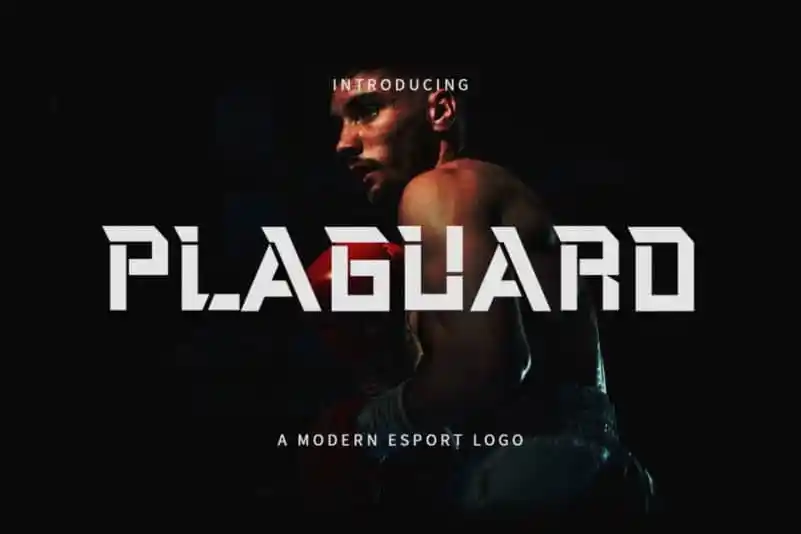
A Plaguard Display Font é uma excelente escolha para quem procura uma fonte de headlines moderna, elegante e versátil. Criação do designer Rometheme, esta fonte traz capas estilizadas para cada letra, resultando em um visual arquitetado para uso em headlines e marcas de ativação. Ela se destaca por sua simplicidade de uso e facilidade de aplicação em projetos variados como fashion, aparelhos, selos, logotipos, marca, revistas e mídia social. Seu design moderno e minimalista faz dela uma ótima opção para qualquer projeto que busque transmitir uma imagem atraente e contemporânea. Suas linhas fortes e limpas combinam com o estilo vintage das capas estilizadas, criando um contraste interessante que destaca seu uso em ambientes digitais e físicos. Com certeza é uma fonte de escolha ideal para qualquer tipo de projeto ou aplicação gráfica onde se espera transmitir uma mensagem poderosa e elegante.